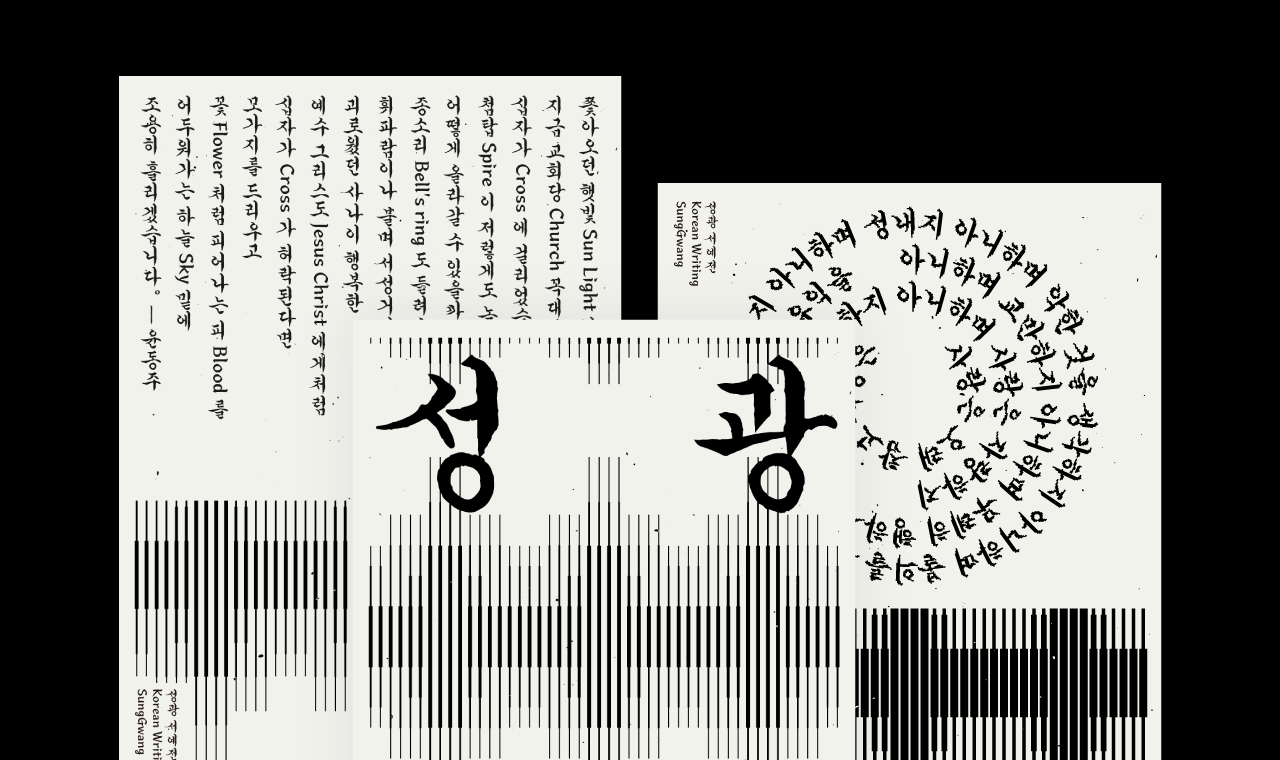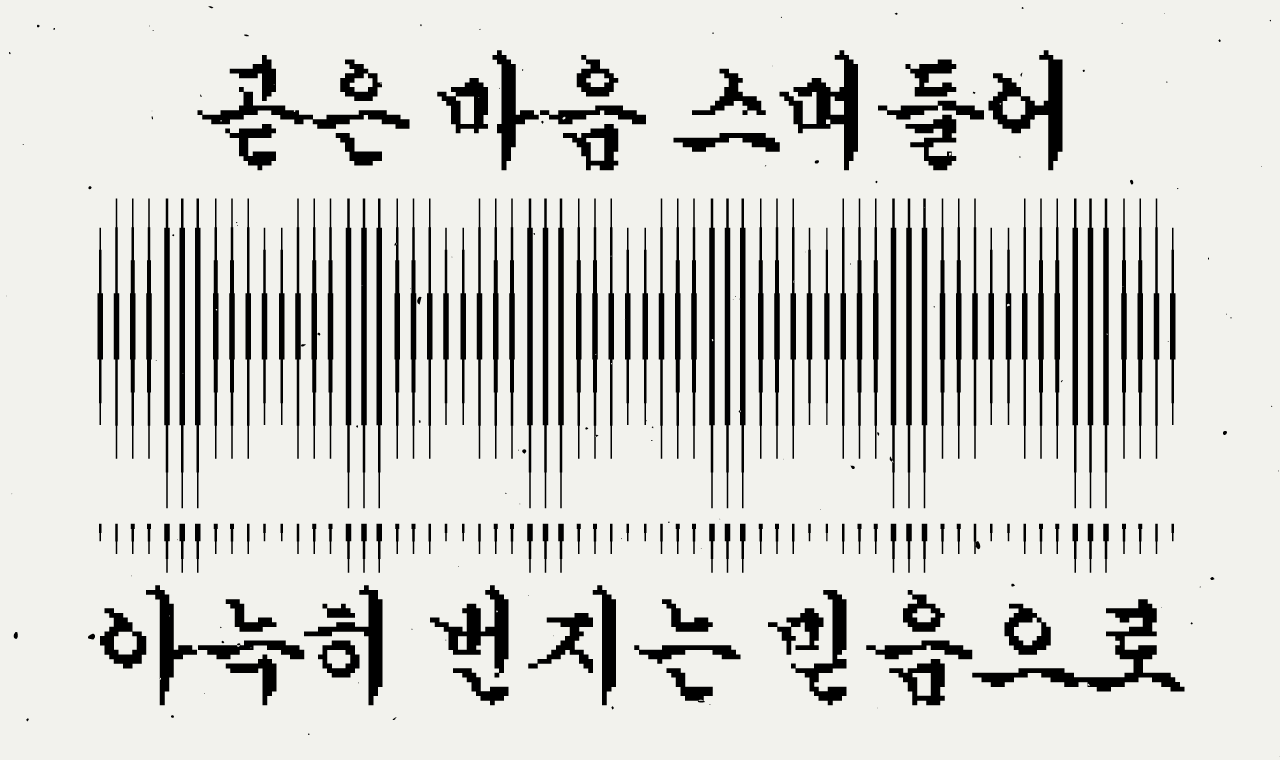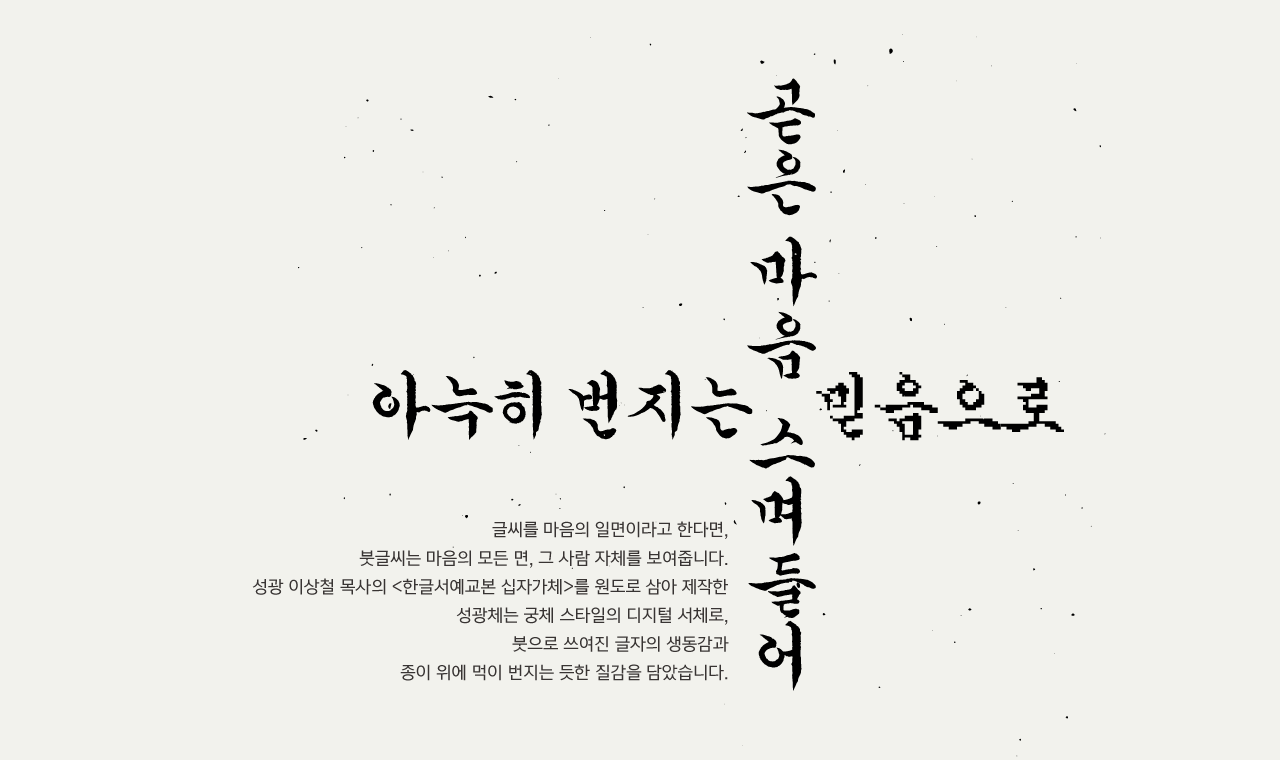
성광체는 성광 이상철 목사의 <한글서예교본 십자가체>를 원도로 삼아 제작한 궁체 스타일의 디지털 서체입니다. 붓으로 쓰여진 글자의 생동감과 종이 위에 먹이 번지는 듯한 질감을 살려 제작했습니다. 글자의 전체적인 형태와 세로모임 중성 ‘ㅜ’가 십자가 모양을 닮아 날카로우면서도 신실한 인상을 줍니다. 숙달된 필력의 붓글씨를 고이 표현한 성광체는 세로쓰기와 가로쓰기, 가로쓰기 Pixel까지 총 3종으로 구성되어 있습니다.